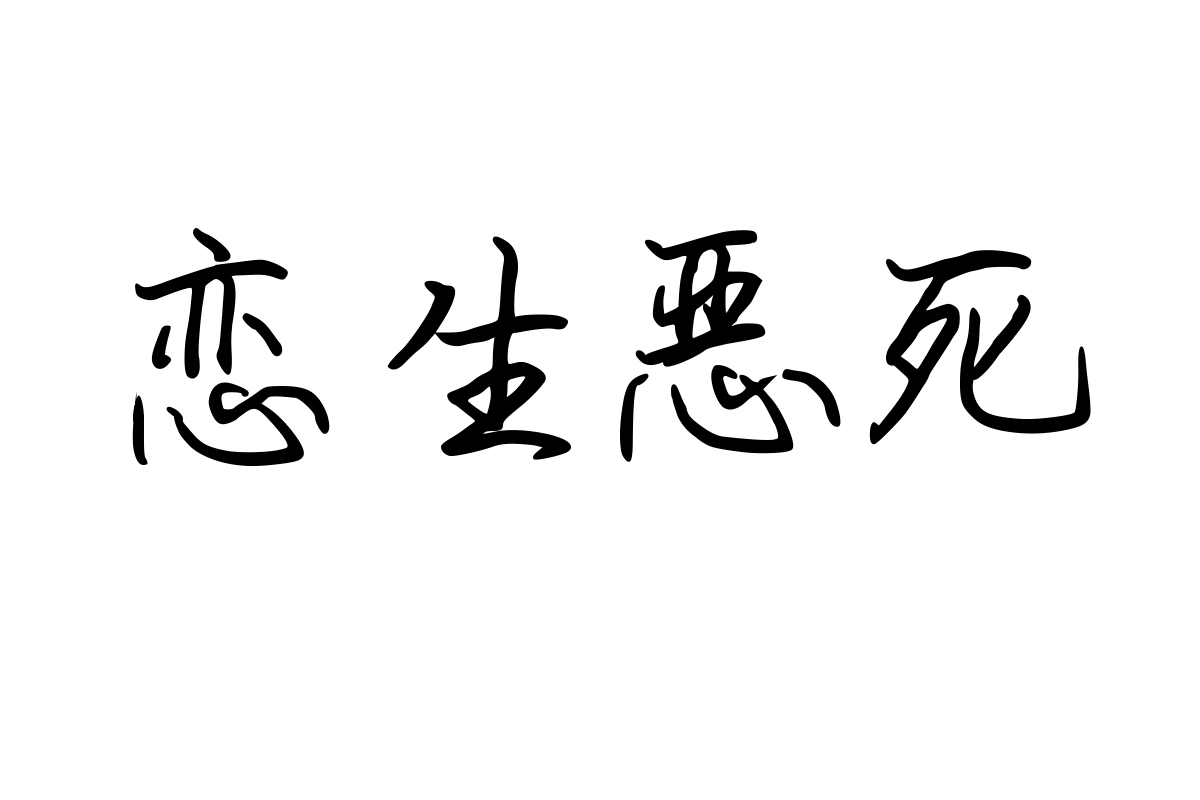
米开潇洒情书体是一种手写字体,其特点是笔画流畅、字形优美。这种字体的特点是线条粗细变化较大,给人一种潇洒的感觉。同时,这种字体的书写速度较快,适合快速书写。
米开潇洒情书体的特点包括:
1. 线条粗细变化大,笔画流畅,给人一种潇洒的感觉。
2. 书写速度快,适合快速书写。
3. 适合用于手写情书,表达深情。